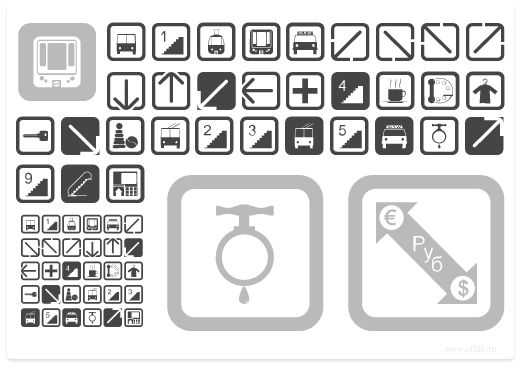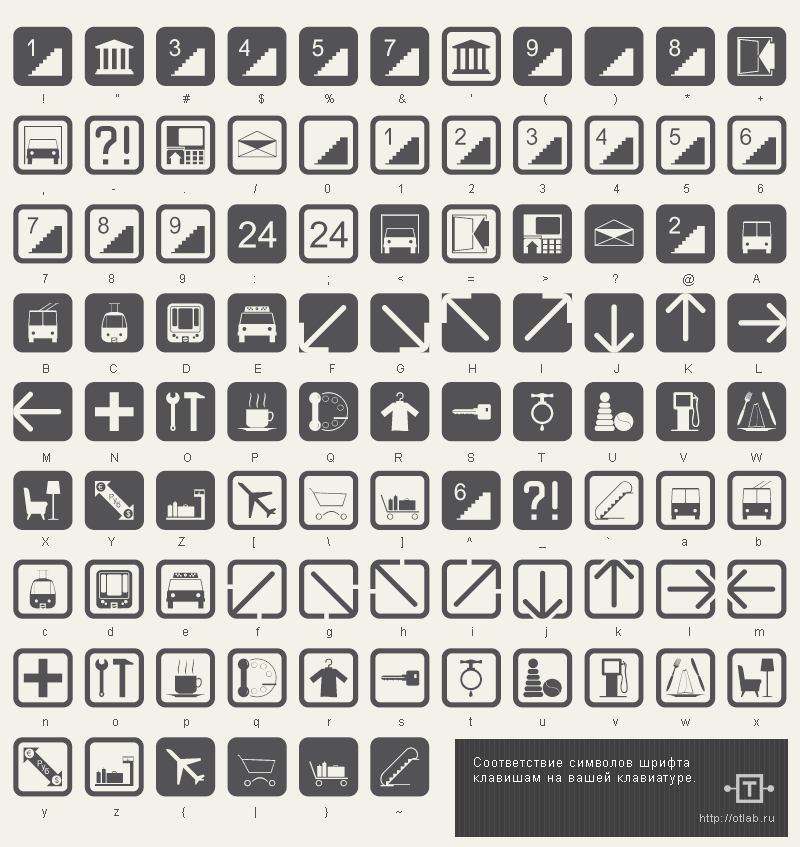
Символьный шрифт Notice2
Продолжение серии шрифтов «Notice». Шрифт содержит ин­фор­мационные значки: «аэрпорт», «ресторан», «почта», «остановка автобуса», «такси», «метро», «банкомат», «кафе», «камера хранения», «мед­пункт», «таксофон» и дру­гие. Пред­наз­на­чен для сос­тав­ле­ния раз­лич­ных схем про­ез­да и на­ви­га­ции. [url=http://otlab.ru/fonts/notice2.html]Скачать шрифт[/url]